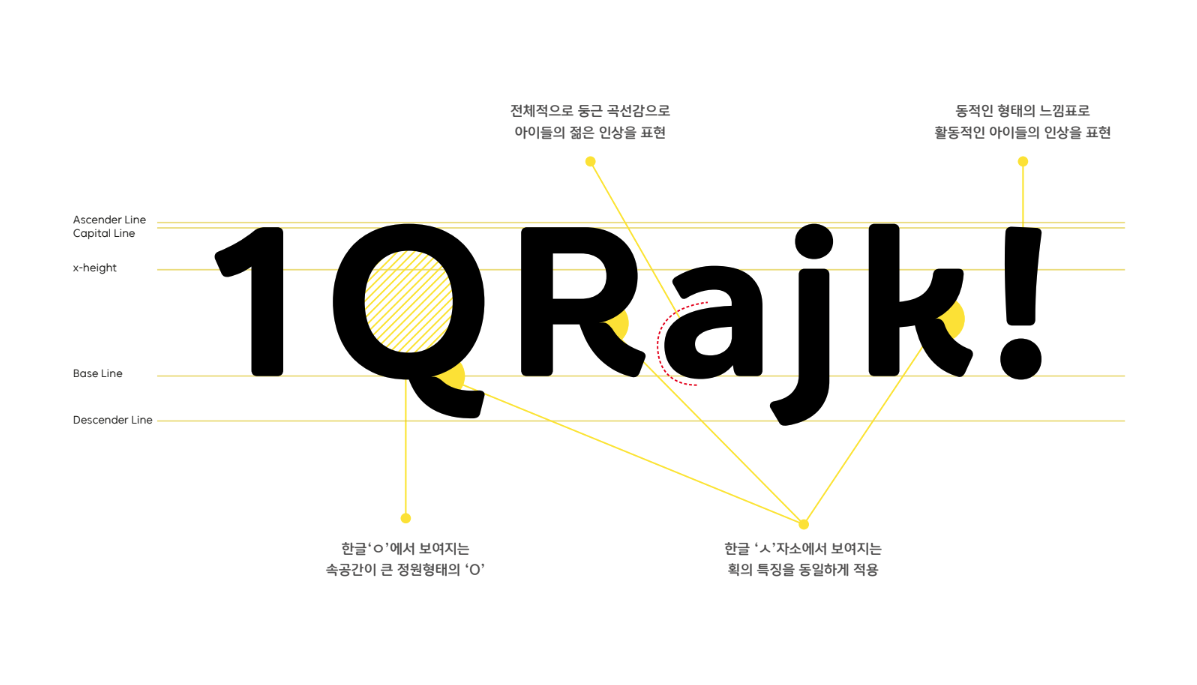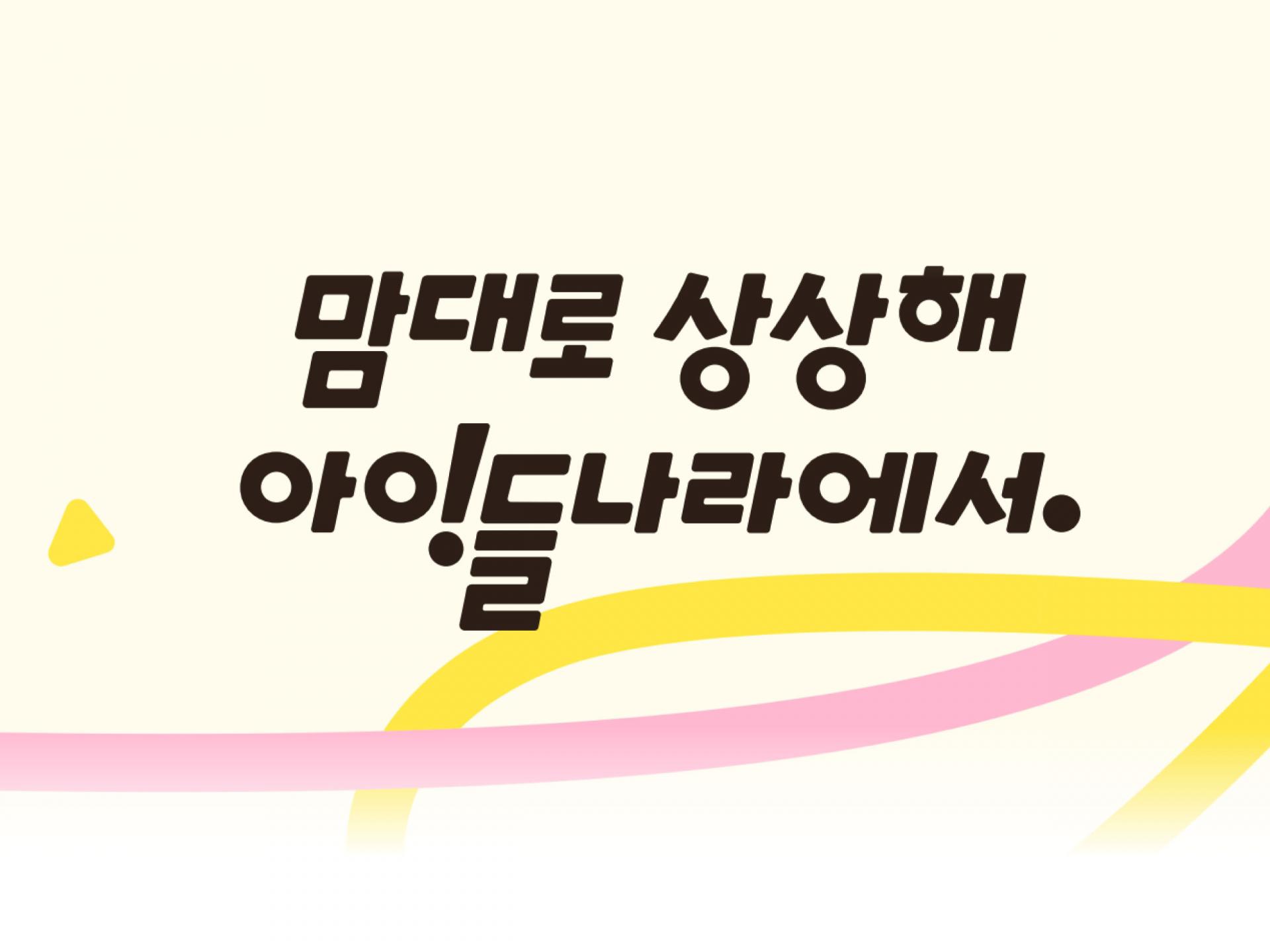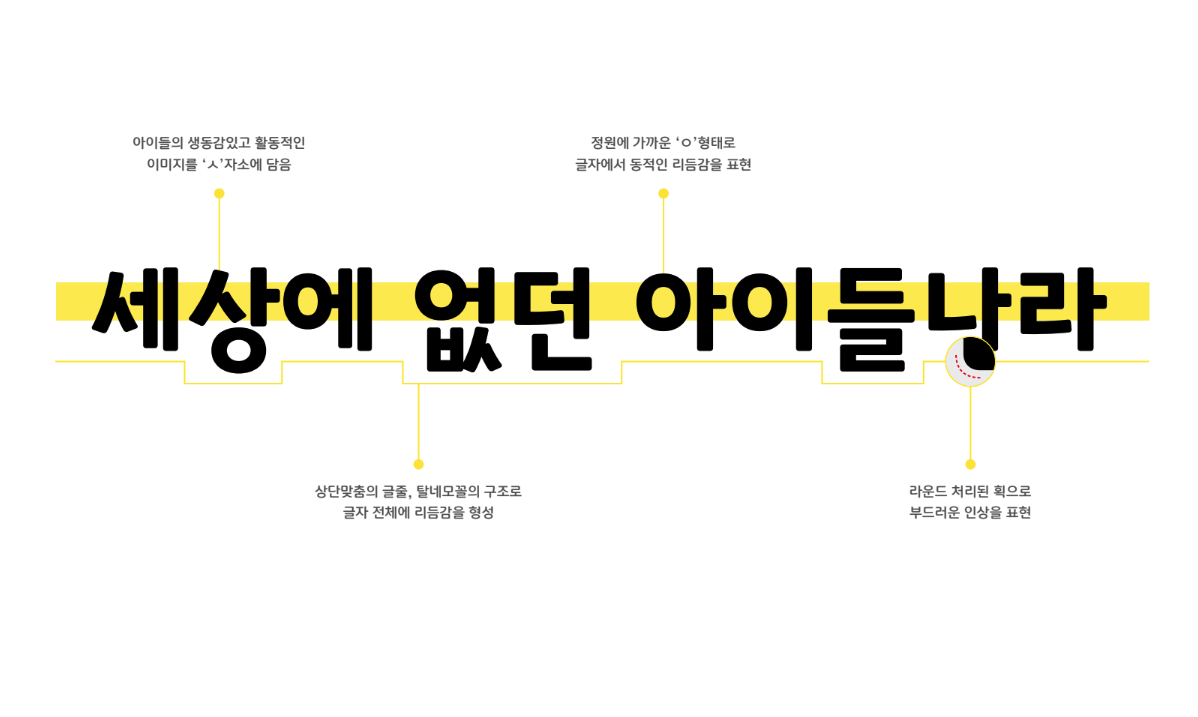
LG U+ 아이들나라 [아이상상체]
LG U+의 대표 키즈 플렛폼, 아이들나라의 전용서체 [아이상상체]는 아이들의 다양한 감정과 활동 안에 잠재된 상상력과 아이들나라만의 고유한 브랜드 아이덴티티를 담아 개발된 로고타입을 기반으로 개발되었다. 장체의 구조 속 짜임새 있는 글자폭과 상단맞춤 글줄 흐름 속 미세한 탈네모 구조를 통해 캐주얼하고 생동감있는 리듬을 형성하는 것이 특징이다.